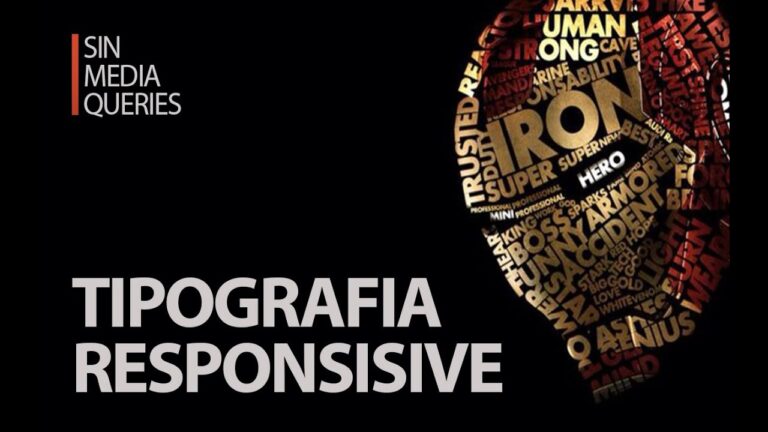
Tipografía Responsive: Clave para un Diseño Web Efectivo
En el mundo del diseño web, la tipografía responsive se ha convertido en un elemento clave para garantizar una experiencia de usuario óptima en diferentes dispositivos. Adaptar el tamaño, el estilo y la legibilidad de las fuentes no solo mejora la estética de una página, sino que también facilita la accesibilidad y la navegación. A medida que más usuarios acceden a la web a través de móviles y tabletas, comprender cómo implementar una tipografía rendidora se vuelve esencial para captar y retener la atención del público. En este artículo, analizaremos las mejores prácticas y herramientas para lograr una tipografía responsive que eleve tu diseño web al siguiente nivel.
¿Qué tipo de letra debería utilizar para un sitio web?
Al elegir la tipografía adecuada para tu sitio web, es fundamental optar por fuentes que sean legibles y visualmente atractivas. Algunas de las opciones más compatibles con la web incluyen Times New Roman, conocida por su elegancia clásica, Arial, que ofrece un diseño limpio y moderno, y Verdana, que destaca por su excelente legibilidad en pantallas. Estas tipografías no solo mejoran la experiencia del usuario, sino que también aportan un toque profesional a tu contenido.
¿Qué significa el diseño web responsivo?
El diseño web adaptable, o "responsive design", es una técnica fundamental en la creación de sitios web modernos. Su objetivo principal es garantizar que el contenido se visualice de manera óptima en una variedad de dispositivos, como tabletas y smartphones. A través de este enfoque, se busca ofrecer una experiencia de usuario fluida y agradable, independientemente del tamaño de la pantalla o la resolución del dispositivo que se esté utilizando.
Implementar un diseño web responsivo no solo mejora la accesibilidad, sino que también contribuye a un mejor posicionamiento en motores de búsqueda. Al adaptarse automáticamente a diferentes formatos, los sitios web pueden cargar más rápido y ofrecer una navegación intuitiva, lo que resulta esencial en un mundo donde cada vez más personas acceden a Internet desde sus dispositivos móviles. En resumen, el diseño responsivo es esencial para cualquier estrategia digital rendidora.
¿Qué tipografías recomendarías por su legibilidad en la web?
Para asegurar una óptima legibilidad en la web, es fundamental elegir tipografías que sean universalmente reconocibles y fáciles de leer. Las fuentes seguras, como Arial, Tahoma, Trebuchet, Verdana, Georgia y Times New Roman, son ideales, ya que vienen preinstaladas en los principales sistemas operativos. Estas opciones no solo garantizan una apariencia uniforme en diferentes dispositivos, sino que también mejoran la experiencia del usuario al facilitar la lectura de contenido en línea.
Adaptabilidad Visual: La Revolución de la Tipografía
En un mundo donde la comunicación visual es fundamental, la tipografía se ha convertido en una herramienta clave para captar la atención y transmitir mensajes de manera rendidora. La adaptabilidad visual en la tipografía permite que los textos se ajusten a diferentes plataformas y contextos, garantizando que la información sea accesible y atractiva. Con una amplia variedad de fuentes y estilos, los diseñadores tienen la libertad de elegir la tipografía que mejor se adapte al contenido, creando una conexión más fuerte con el público.
La evolución de la tecnología ha potenciado esta revolución tipográfica, admitiendo a los diseñadores experimentar con fuentes dinámicas que responden a las interacciones del usuario. Las tipografías ahora no solo son estáticas; pueden cambiar de tamaño, forma y color en tiempo real, mejorando la experiencia del lector. Esta flexibilidad no solo enriquece la estética visual, sino que también optimiza la legibilidad, haciendo que incluso los textos más complejos sean fáciles de entender.
A medida que avanzamos hacia un futuro más digital, la adaptabilidad visual se perfila como un elemento esencial en el diseño. Las marcas que incorporan tipografías versátiles no solo se destacan en un mar de información, sino que también demuestran una comprensión profunda de las necesidades de su audiencia. Así, la tipografía se transforma en un puente entre la creatividad y la funcionalidad, estableciendo nuevas normas en la comunicación visual que capturan y mantienen la atención del espectador.
Diseño que Comunica: La Importancia de la Tipografía Responsive
En el mundo digital actual, la tipografía responsive se ha convertido en un elemento esencial para garantizar una comunicación rendidora. A medida que los usuarios acceden a contenido a través de diversos dispositivos, desde smartphones hasta tablets y computadoras, la forma en que se presenta el texto puede influir sustancialmente en la experiencia del usuario. Una tipografía bien diseñada se adapta no solo al tamaño de la pantalla, sino también al contexto de lectura, asegurando que la información sea fácilmente accesible y comprensible para todos.